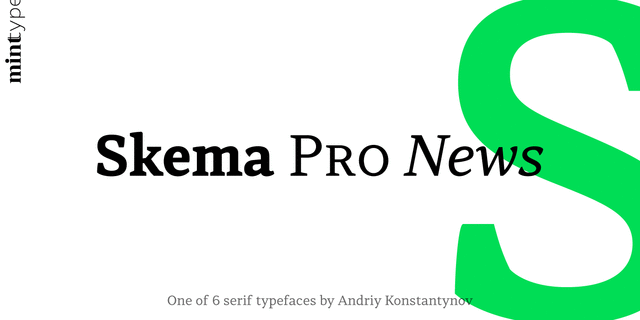
Skema Pro News – малоконтрастная гарнитура с большой высотой строчных и вертикальной осью. Предназначена для использования в газетах и экранных текстах.
Skema Pro – система из 6 антикв, каждая из которых имеет свой характер и назначение. Вместе они формируют огромную супергарнитуру из 84 начертаний для любых возможных задач.
Семейство Skema Pro разработал и выпустил Андрей Константинов в студии Mint Type в 2017 году.